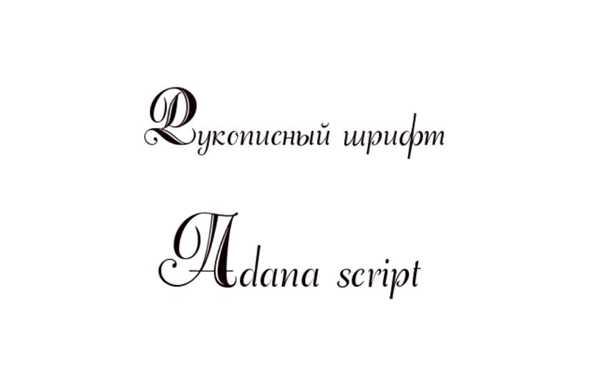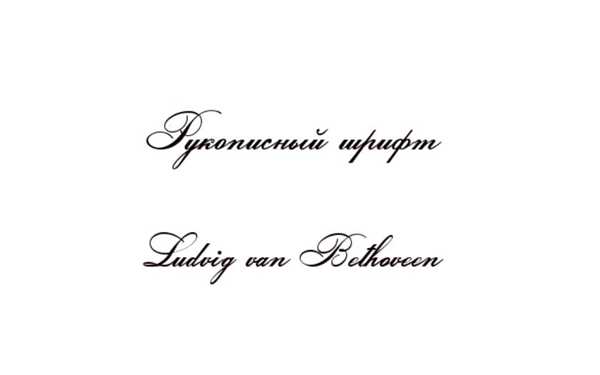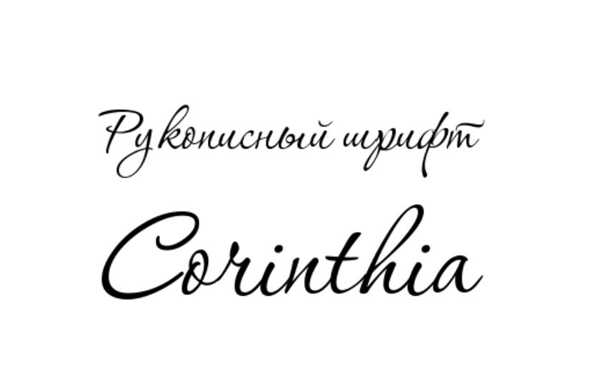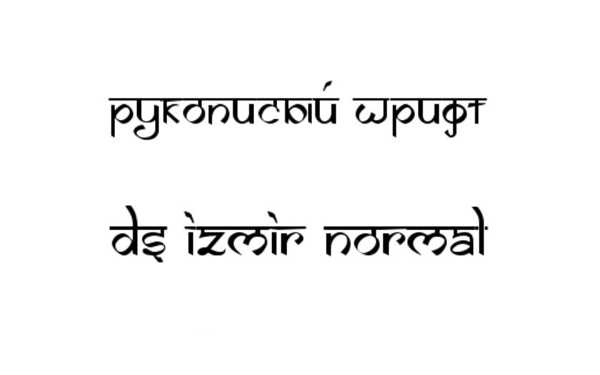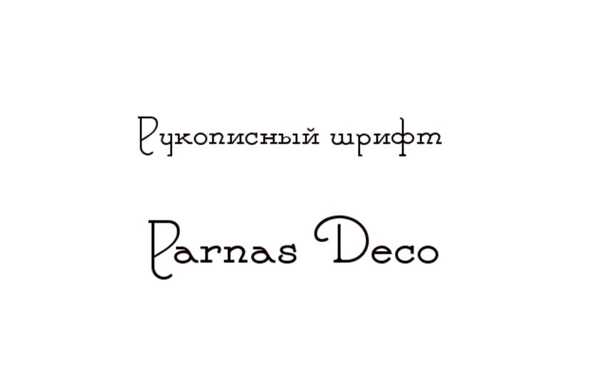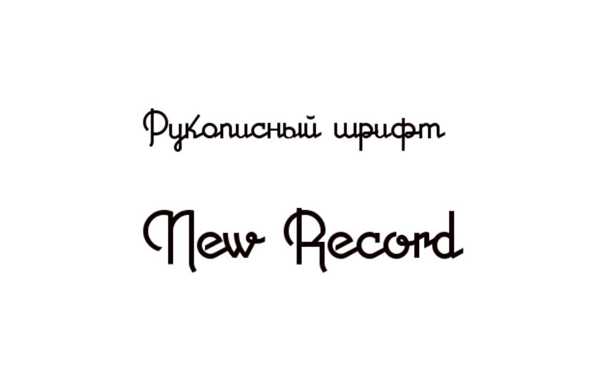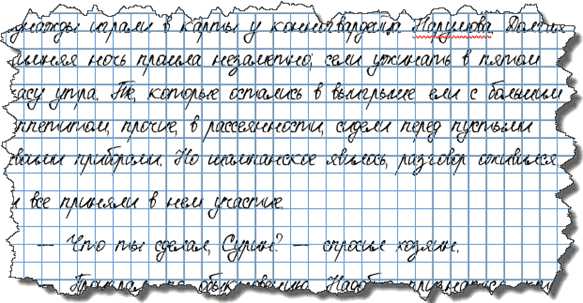
Шрифт рукописный для ворда – Рукописные шрифты — русские скачать бесплатно
Как сделать рукописный шрифт в Ворде, установив его на компьютер
Рукописный шрифт (скрипт) — это не только красивое декоративное письмо. В школах и других учебных заведениях часто задают массу письменных упражнений. Оказывается, их тоже можно выполнять с помощью клавиатуры.
Каллиграфическим почерком, выполненным на компьютере, оформляются официальные документы, почетные грамоты. Помимо создания стиля, дизайна текста имеется возможность изготавливать прописи для детей.
Есть способ синтезировать собственное письмо или имитировать почерк любого человека. Рассмотрим, где используется и как сделать рукописный шрифт в Ворде.
Что считают рукописным шрифтом, виды
Рукописным называют шрифт, написанный от руки. Сейчас можно имитировать его на компьютере в текстовых редакторах. Прежде, чем узнать, как сделать рукописный шрифт в Ворде, ознакомимся с видами скриптов.
Наш почерк — это рукописный шрифт
Существует классификация в зависимости от того, какое письмо изображается. К примеру, выполненное:
- остроконечным или ширококонечным пером;
- кистью;
- карандашом;
- маркером;
- ручкой;
- другими пишущими инструментами.
При разном оформлении скрипты отличаются один от другого аккуратностью, жирностью линий. Различают формальный и казуальный типы. Первый — типичное начертание с ровной толщиной линий, используемое писателями прошлых веков.
Это Palace Script или близкие к школьным прописям Olga, Propisi. Казуальный скрипт более современен, свободен, с линиями разной толщины. Имитирует рекламное письмо кистью, гравировку. Примерами являются элегантные Decor, Corrida, Brush Script.
Рукописные шрифты (или скрипты) бывают связные, когда все буквы соединены между собой. А также не связанные при отдельной расстановке каждого элемента и промежуточные формы.
Для чего может понадобиться рукописный шрифт
Весьма красиво выглядит письмо, выполненное на компьютере одним из рукописных шрифтов. Без подобного оформления надписей на фотографиях, иллюстрациях и баннерах не обходится компьютерная графика.
Рукописные шрифты выглядят довольно эффектно
Подобные скрипты предназначены для имитации прописи и рукописи. Они применяются в полиграфической акциденции (наборе).
То есть для воспроизведения бланков, грамот, аттестатов, ярлыков, как малых форм, плакатов и афиш.
Кроме того, используются для производства учебной литературы. Как сделать рукописный шрифт в Ворде и для чего затем применить?
Возьмем для примера скрипт Primo, имитирующий каллиграфию. Именно с его помощью создаются школьные прописи, которые можно сделать собственноручно в программе Microsoft Word.
Для установки на компьютер необходимо найти и выбрать шрифт в Интернете. Primo несколько сложен в установке, требует дополнительных приложений (макросов). Но предлагается множество других, аналогичных и резко отличающихся один от другого. Кто-то предпочитает эстетику для дизайна.
Надписи должны легко читаться, быть понятными, особенно, если с помощью конкретного скрипта оформляется документ. Поэтому для текстового редактора более подходит простой и практичный стиль.
Если операционная система (ОС) укомплектована рукописными шрифтами, появится возможность создавать открытки, презентации, надписи на иллюстрациях, декоративное письмо. Как сделать рукописный шрифт в Ворде, рассмотрим далее.
После добавления на компьютер они появляются во всех программах, где используется письменность, в редакторах текстов и фото. Интернет бесплатно предлагает для скачивания множество скриптов.
Они функционируют с кириллицей или латиницей, но есть и универсальные варианты. Для установки нужно сначала найти по запросу «шрифты» и скачать файл. Формат — TTF или OTF.
В ранних версиях ОС Windows требовалось лишь скопировать его в директорию для шрифтов. Это C:\Windows\Fonts. Затем можно было пользоваться скриптом через редакторы. Сейчас процесс упростился до следующих шагов:
- Нажимаем на скачанный файл шрифта в папке «Загрузки».
- Правой кнопкой мыши открываем меню и выбираем «Установить».
- Теперь шрифт появится, готовый к использованию в любом редакторе, в том числе Microsoft Word.
Если все-таки вновь установленный рукописный алфавит ещё не заработал, нужно перезагрузить компьютер. Примерами скриптов для загрузки может быть Shlapak Script, Good Vibes Pro, Liana. Теперь должно быть понятно, как сделать рукописный текст в Ворде.
Собственный шрифт, имитация почерка
Помимо скачивания готовой подборки можно создать свой рукописный шрифт. Для этого нужно установить специальную программу: Font Creator или High-Logic FontCreator (Разработчик шрифтов).
Любой может создать свой шрифт, сымитировав конкретный почерк
Попробуйте Mistral думаю это то, что вам нужно!
Стиль Mistral поставь
КИРИЛЛИЦА: MONOTYPE CURSIVA, SEGOE SCRIPT/PRINT, GABRIOLA, FANG SONG Латиницы там много…
надо выбрать шрифт Segoe Script (реально работает я говорю чеснопрямо как настоящий)